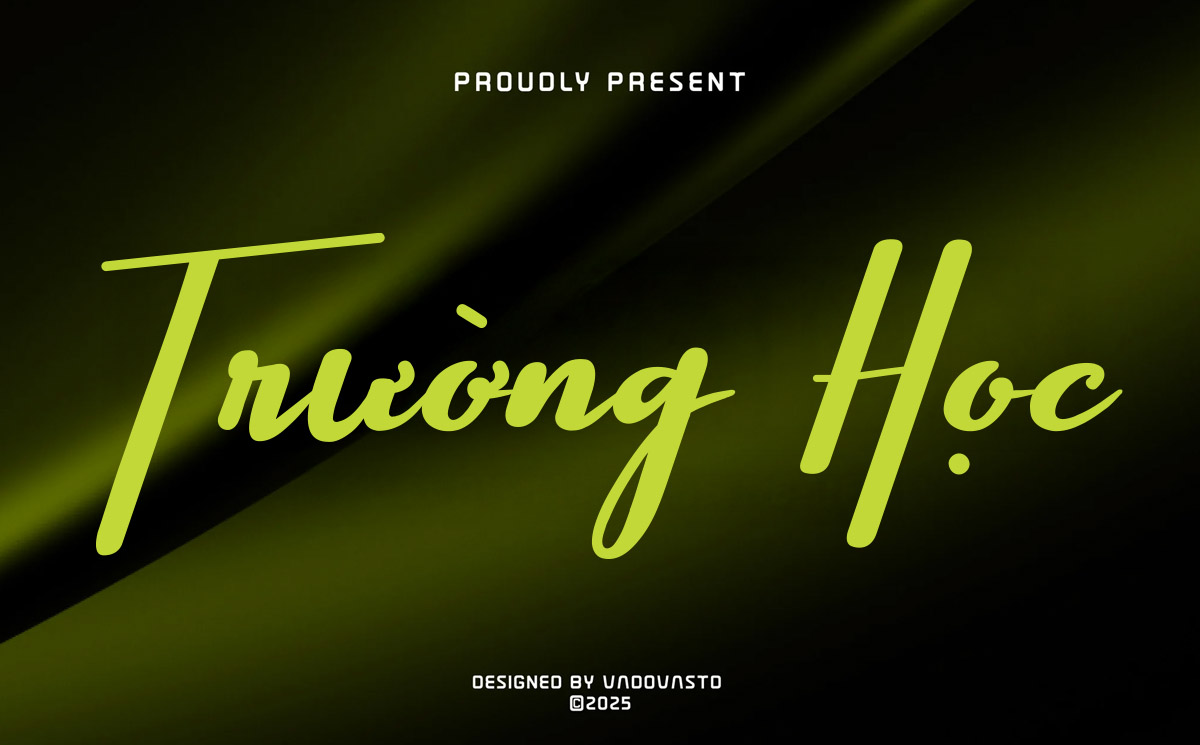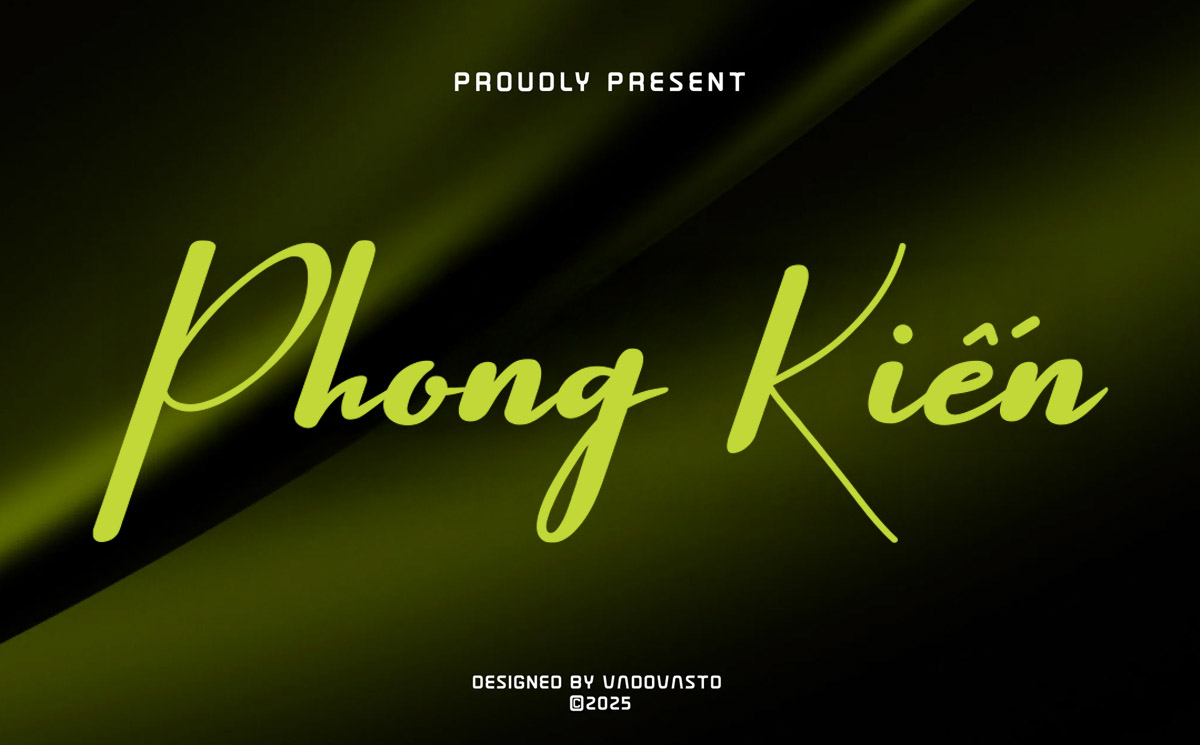
[Tải Xuống] Bộ Sưu Tập 15 Font Chữ Script Việt Hóa Được Ưa Chuộng Nhất 2025
Bạn đang tìm một font chữ viết tay Việt hóa mềm mại, nghệ thuật cho thiệp cưới, logo hay thiết kế chữ ký cá nhân? Font chữ script Việt hóa chính là lựa chọn lý tưởng. Bài viết này tổng hợp 15 font script Việt hóa đẹp nhất 2025, đầy đủ phong cách – từ thư pháp cổ điển đến viết tay hiện đại – kèm link tải xuống từ S99.vn.
Font chữ Script là gì?
Font chữ Script là một dạng phông chữ mô phỏng nét viết tay – thường có đặc trưng là đường cong mềm mại, uyển chuyển, liền nét và giàu tính biểu cảm. Đây là kiểu font mang lại cảm giác cá nhân, gần gũi và nghệ thuật, thường được lấy cảm hứng từ thư pháp hoặc chữ viết tay tự nhiên.
Đặc điểm nổi bật của font chữ Script
• Nét chữ uốn lượn như viết bằng bút lông, bút mực.
• Chữ thường nối liền nhau (cursive), tạo nên dòng chảy liên tục.
• Có thể mang phong cách thanh lịch, cổ điển hoặc phóng khoáng, hiện đại tùy từng biến thể.
Phân loại các nhóm phổ biến trong font chữ Script
Calligraphy Script – Thanh mảnh, thư pháp cổ điển
Font Calligraphy được lấy cảm hứng từ nghệ thuật viết thư pháp truyền thống. Đặc trưng với:
• Các nét mảnh mai, dẻo dai, có độ nghiêng nhẹ, mô phỏng chuyển động thật của bút lông.
• Thể hiện sự sang trọng, trang nhã và tinh tế.
• Rất phù hợp cho các thiết kế thiệp cưới, logo thương hiệu cao cấp, danh thiếp, hay những ấn phẩm mang tính truyền thống.
Dưới đây là một số ví dụ về nhóm font chữ Calligraphy Script:
FZ Tiểu Tự - Thư Pháp Việt Nam
Font chữ thư pháp FZ Tiểu Tự là một kiểu chữ được thiết kế tỉ mỉ, mô phỏng sát các nét thư pháp viết tay truyền thống. Font này mang đậm phong cách nghệ thuật thư pháp, với các đường nét uyển chuyển, mềm mại và giàu tính biểu cảm. Các ký tự trong font được chăm chút kỹ lưỡng, phản ánh sự tinh tế và công phu của nghệ thuật viết chữ đẹp.
Font FZ Tiểu Tự phù hợp cho các thiết kế mang tính truyền thống như thiệp chúc mừng, câu đối Tết, hoặc các dự án cần sự trang trọng và nghệ thuật. Với sự kết hợp giữa tính thẩm mỹ và tính ứng dụng cao, đây là lựa chọn lý tưởng cho những ai yêu thích và muốn thể hiện vẻ đẹp của thư pháp trong thiết kế hiện đại.​
TH Hildesheim – Viết tay cổ điển, mạnh mẽ
Font chữ trong ảnh mang phong cách monoline script, với các đặc điểm đường nét thanh thoát, mượt mà và liền mạch. Đây là một kiểu font viết tay mang tính nghệ thuật, với các đường cong nhẹ nhàng và đều đặn, tạo cảm giác mềm mại và thanh thoát. Những nét chữ này có sự kết hợp giữa sự uyển chuyển của chữ viết tay và tính đơn giản của phông chữ monoline (chỉ sử dụng một độ dày đường nét), làm nổi bật sự sang trọng và tinh tế.
Phông chữ này phù hợp cho các thiết kế cần sự nhẹ nhàng, lãng mạn, ví dụ như thiệp cưới, thiệp mời, logo thương hiệu cao cấp hoặc các dự án sáng tạo có tính cá nhân cao. Những đường nét đơn giản, nhưng vẫn giữ được sự thanh thoát và nghệ thuật, giúp font chữ này nổi bật mà không quá phức tạp.
TH Flarida – Viết tay uốn lượn nghệ thuật
Font chữ Flarida là một font viết tay mềm mại và tinh tế, là một sự lựa chọn tuyệt vời cho những thiết kế mang đậm chất lãng mạn và sang trọng. Được thiết kế với các đường nét uốn lượn thanh thoát, Flarida mang lại một không khí nhẹ nhàng và tao nhã, thích hợp cho các sự kiện trọng đại như đám cưới. Font này không chỉ làm nổi bật vẻ đẹp tự nhiên và uyển chuyển qua từng nét chữ, mà còn giữ được sự thanh lịch, làm cho nó trở thành sự lựa chọn lý tưởng để trang trí cho thiệp cưới, thiệp mời, và các ấn phẩm khác liên quan đến hôn lễ.
TH Cadillac – Viết tay cao cấp, dùng cho logo
Font chữ TH Cadillac Việt hóa là một kiểu chữ viết tay mang phong cách cổ điển và sang trọng, được lấy cảm hứng từ logo thương hiệu Cadillac nổi tiếng. Với đường nét uốn lượn mềm mại, font thể hiện sự duyên dáng và thanh lịch trong từng ký tự. Các chữ cái được thiết kế nghiêng nhẹ, tạo cảm giác chuyển động uyển chuyển và rất thích hợp cho những thiết kế cần sự tinh tế như thiệp cưới, chữ ký cá nhân, logo hoặc tiêu đề mang tính nghệ thuật. Font có độ dày nét mảnh, thanh thoát, giúp văn bản trở nên nhẹ nhàng nhưng vẫn nổi bật. Với sự kết hợp giữa vẻ cổ điển và sự mềm mại hiện đại, TH Cadillac Việt hóa là lựa chọn lý tưởng cho các dự án thiết kế đề cao yếu tố thẩm mỹ và cảm xúc cá nhân.
Casual Script – Gần gũi, thoải mái và tự nhiên
Font thuộc nhóm casual script mang hơi hướng “viết vội nhưng có gu”, thường được thiết kế:
• Với nét viết tròn, to hơn, dễ đọc hơn so với calligraphy.
• Không quá chỉnh chu, thể hiện sự tự nhiên, thân thiện và có phần ngẫu hứng.
• Phù hợp với các thiết kế vui nhộn, poster dành cho giới trẻ, bao bì handmade, hoặc blog cá nhân.
Dưới đây là một số ví dụ về nhóm font chữ Casual Script:
TH Rigidity – In đậm, mạnh mẽ, hiện đại
Font chữ TH Rigidity Việt hóa là một kiểu chữ viết tay đậm nét, mang phong cách cổ điển kết hợp với sự hiện đại, tạo nên vẻ đẹp mạnh mẽ và tinh tế. Với các nét chữ dày và liền mạch, font này thể hiện sự tự tin và nổi bật, phù hợp cho các thiết kế cần gây ấn tượng mạnh như tiêu đề, logo, bao bì sản phẩm và các ấn phẩm quảng cáo. Đặc biệt, TH Rigidity đã được Việt hóa hoàn chỉnh, hỗ trợ đầy đủ các ký tự tiếng Việt có dấu, đảm bảo tính thẩm mỹ và dễ đọc trong các thiết kế sử dụng tiếng Việt.
Kết luận
Font chữ script giúp thể hiện cảm xúc và cá tính một cách tinh tế trong thiết kế. Với 15 lựa chọn Việt hóa đẹp nhất 2025, bạn có thể dễ dàng tạo nên những ấn phẩm độc đáo, sáng tạo và đậm chất riêng.